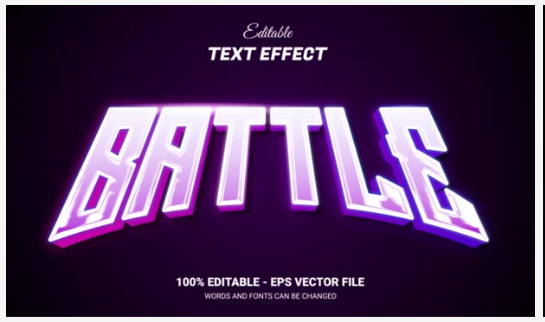
Tổng Hợp Battle Font
Battle Font là những kiểu chữ được thiết kế để truyền tải cảm giác mạnh mẽ, quyết liệt và đầy khí thế. Thuộc bộ font chữ design Với các đường nét góc cạnh, đậm nét và đôi khi có hiệu ứng cũ kỹ, chúng tạo nên một ấn tượng mạnh mẽ, phù hợp với các thiết kế trong lĩnh vực game, phim ảnh, âm nhạc và các thương hiệu thể thao. Sự bất đối xứng và các hiệu ứng đặc biệt giúp tăng cường tính cá tính và sự nổi bật của font chữ, thu hút sự chú ý của người xem.